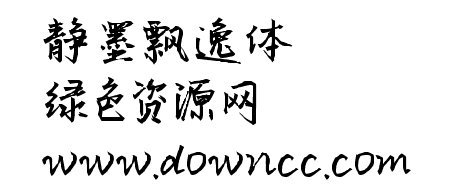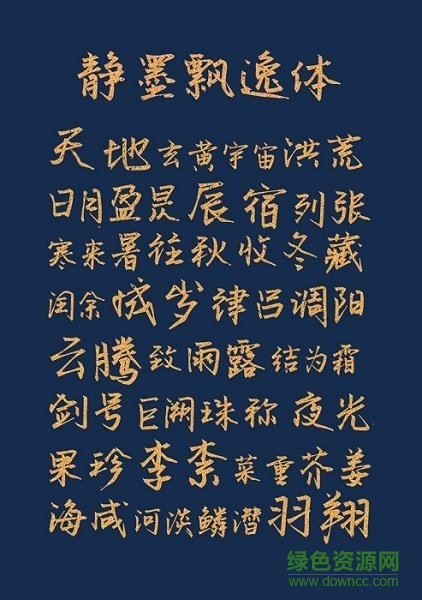
靜墨飄逸體是張默陌推出的一款干練精簡的毛筆飛白書法字體,整體有著極佳的古風(fēng)字體韻味,讓你的文字更加大氣飄揚,形態(tài)多樣十分出色,喜歡的朋友就來綠色資源網(wǎng)體驗吧!
靜墨飄逸體是一款字形渾厚,鋒芒凌厲的毛筆字體,粗獷的線條和飄逸的造型賦予字體張揚靈動的個性,適用于海報、影視等大標題應(yīng)用。
靜墨飄逸體出自默陌字體系列,字體采用毛筆字體的特色風(fēng)格,給人筆觸有力、流暢不羈的特色美感,讓你的平面設(shè)計、包裝設(shè)計更加出色。